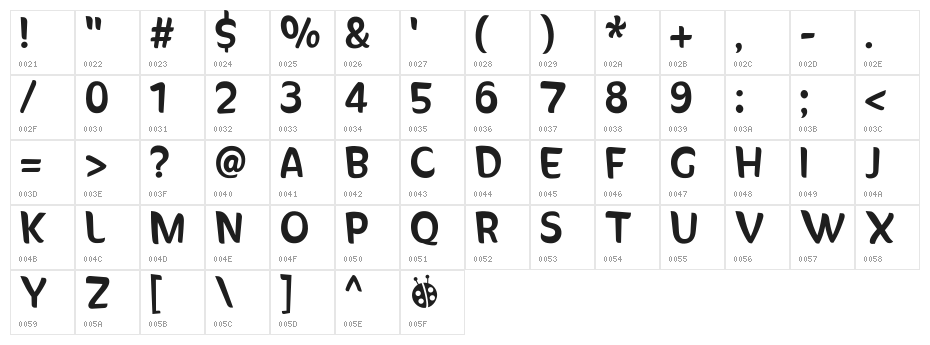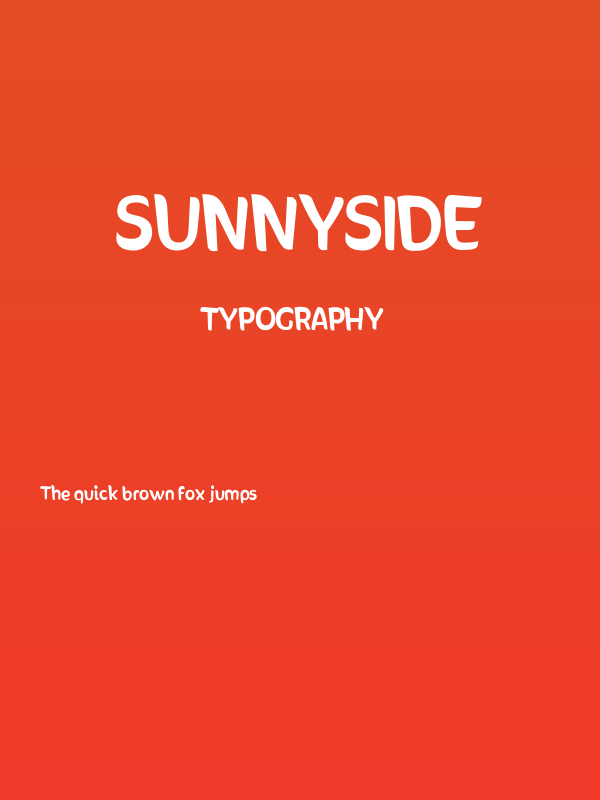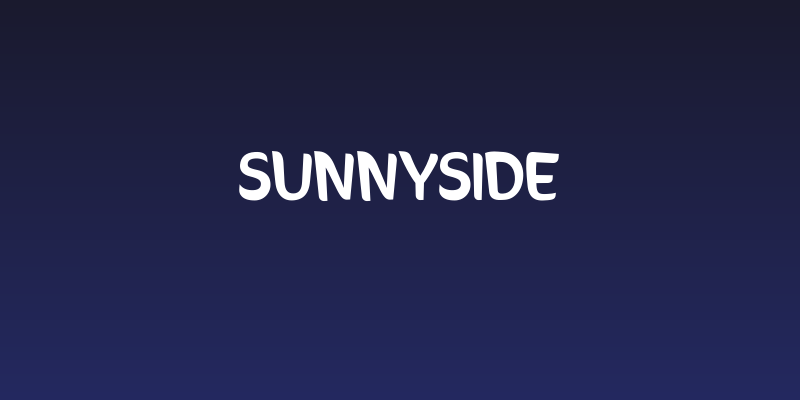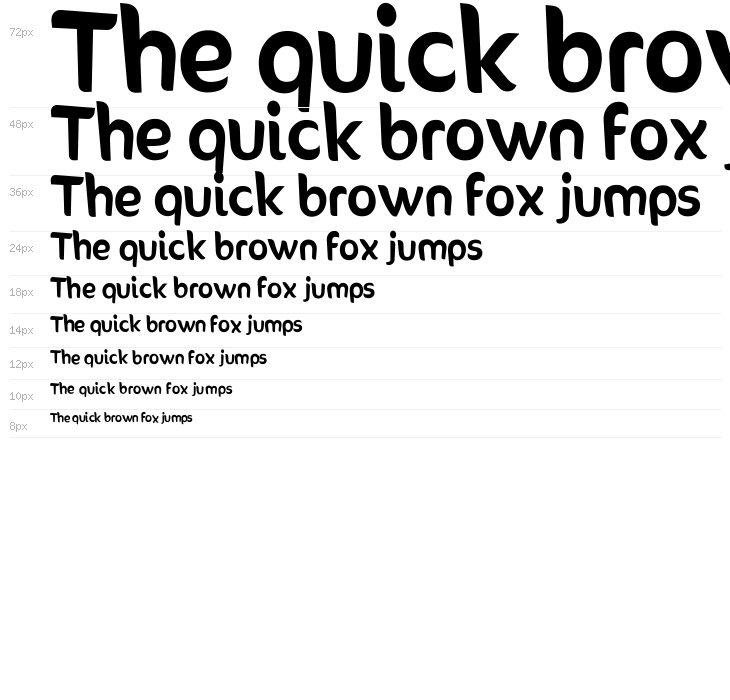
SunnySide Font
SUNNYSIDE Groß
SUNNYSIDE Kleinbuchstaben
SUNNYSIDE Anderer Schreiben
| Vorgeschlagene Projekte | Ideal for children's books, playful branding, casual invitations, and friendly advertising campaigns. |